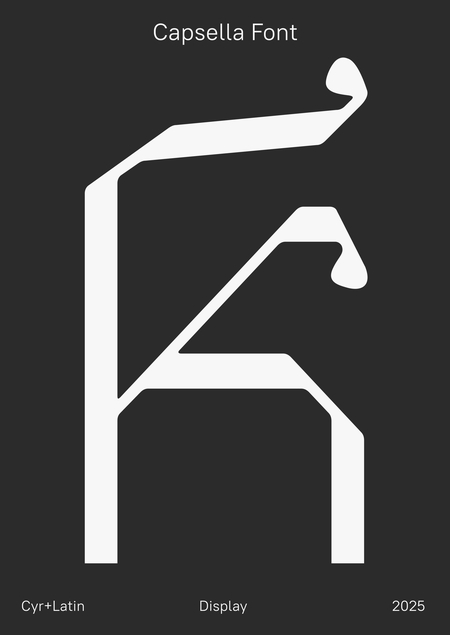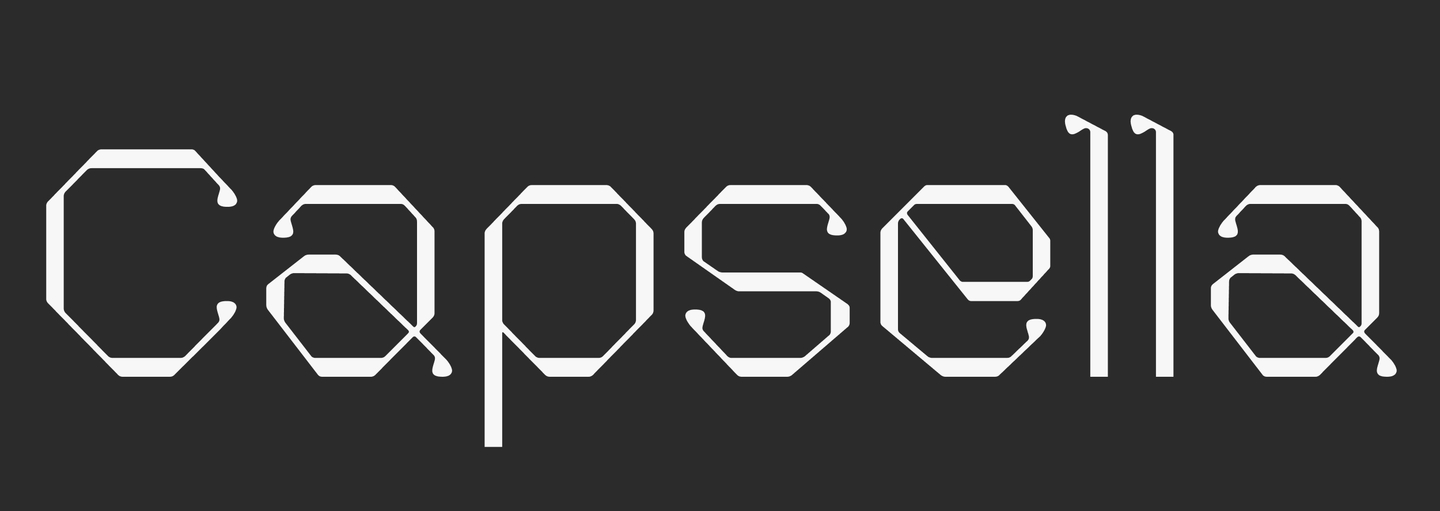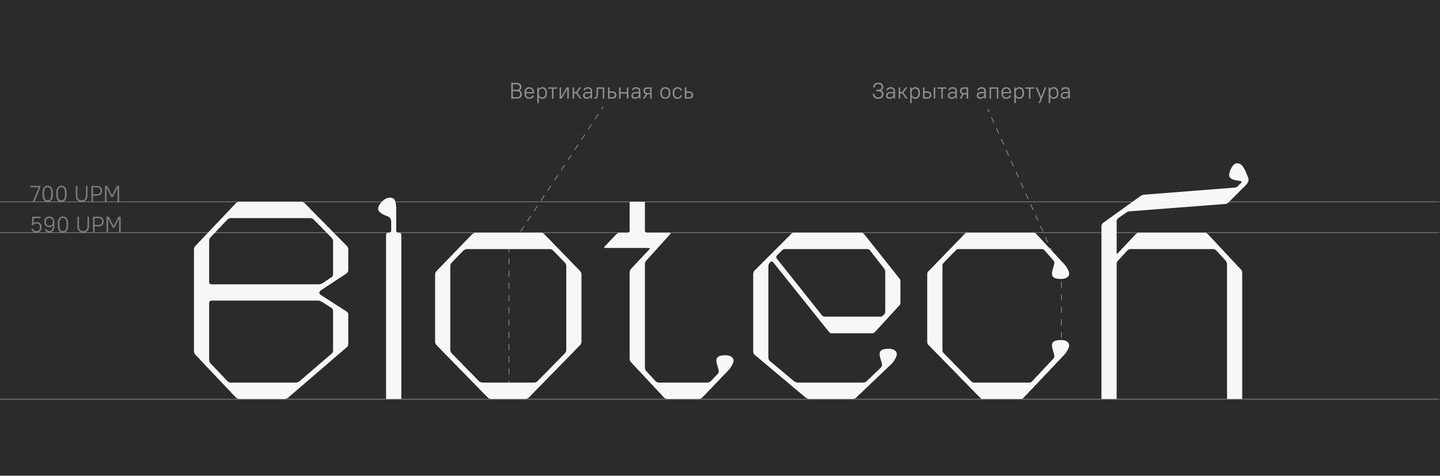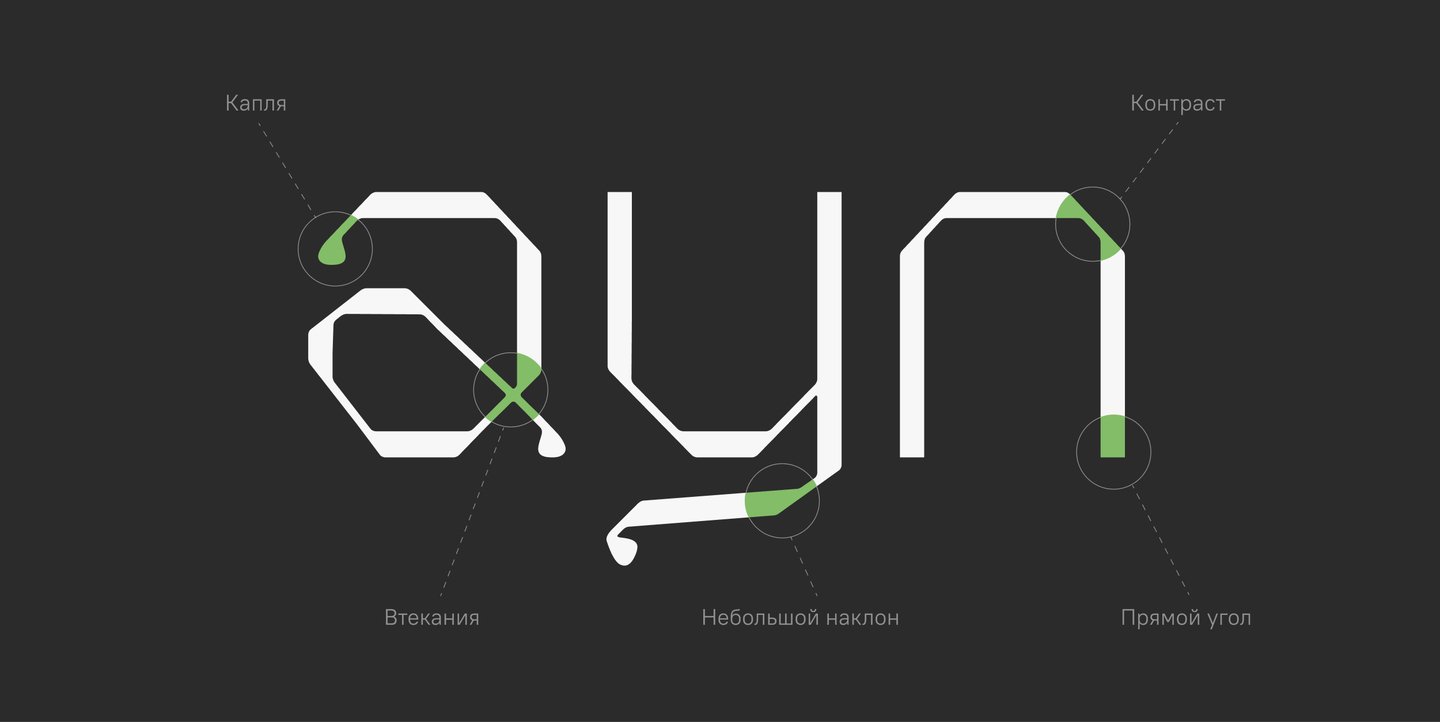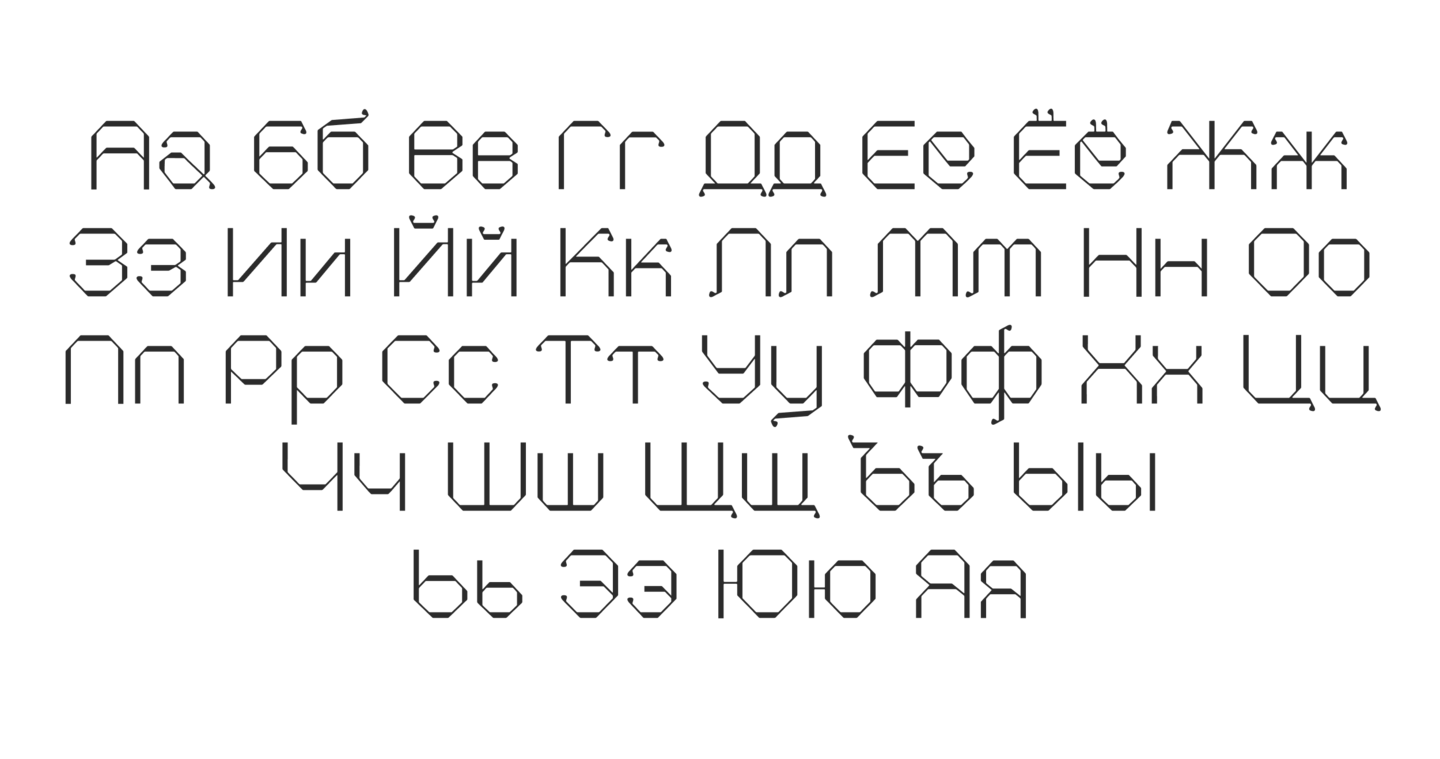
Capsella Font
Акцидентный шрифт, сочетающий технологичную строгость и природную мягкость
Капли букв напоминают семена растения Capsella (пастушья сумка), а строчные почти догоняют прописные по высоте — игра слов с «caps» в названии подчёркивает связь формы и имени шрифта